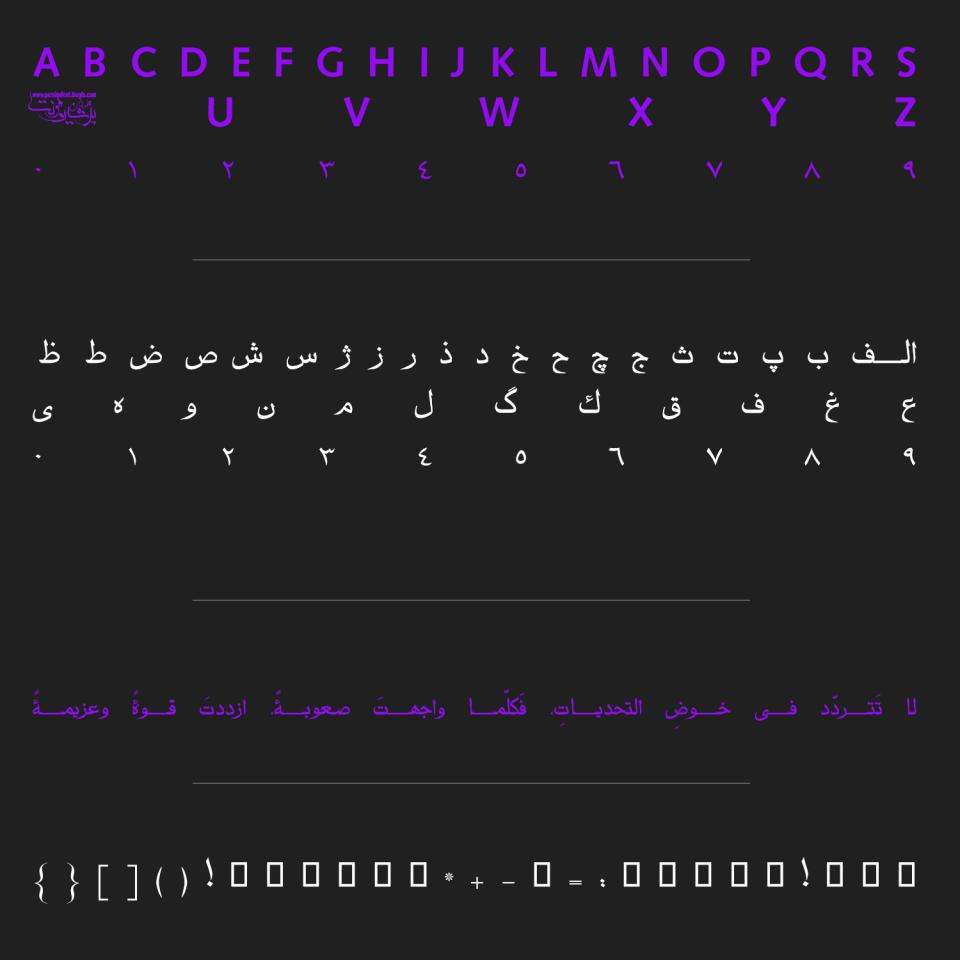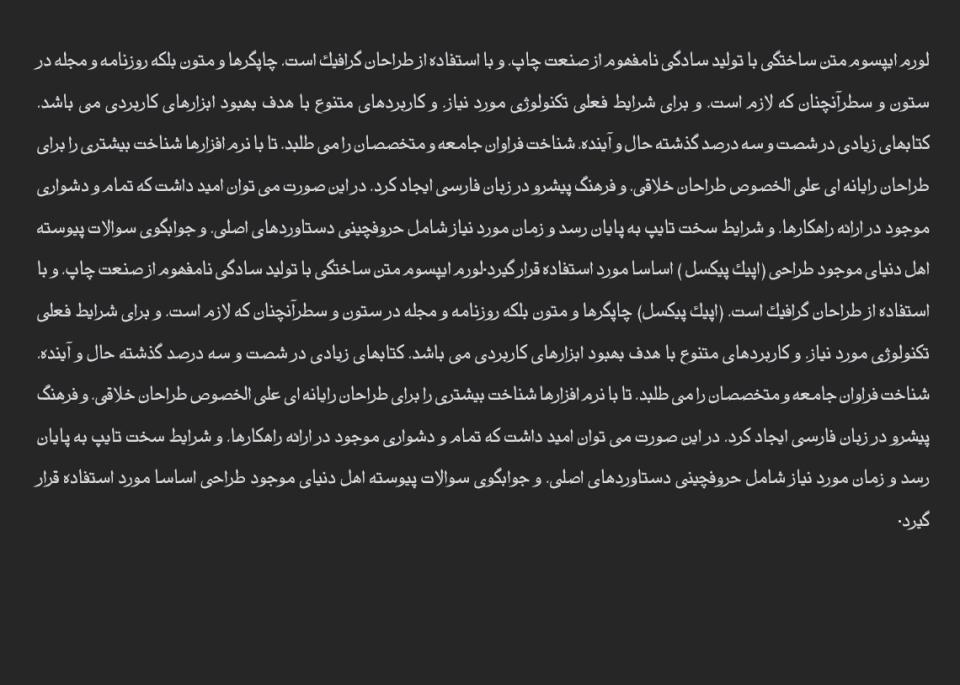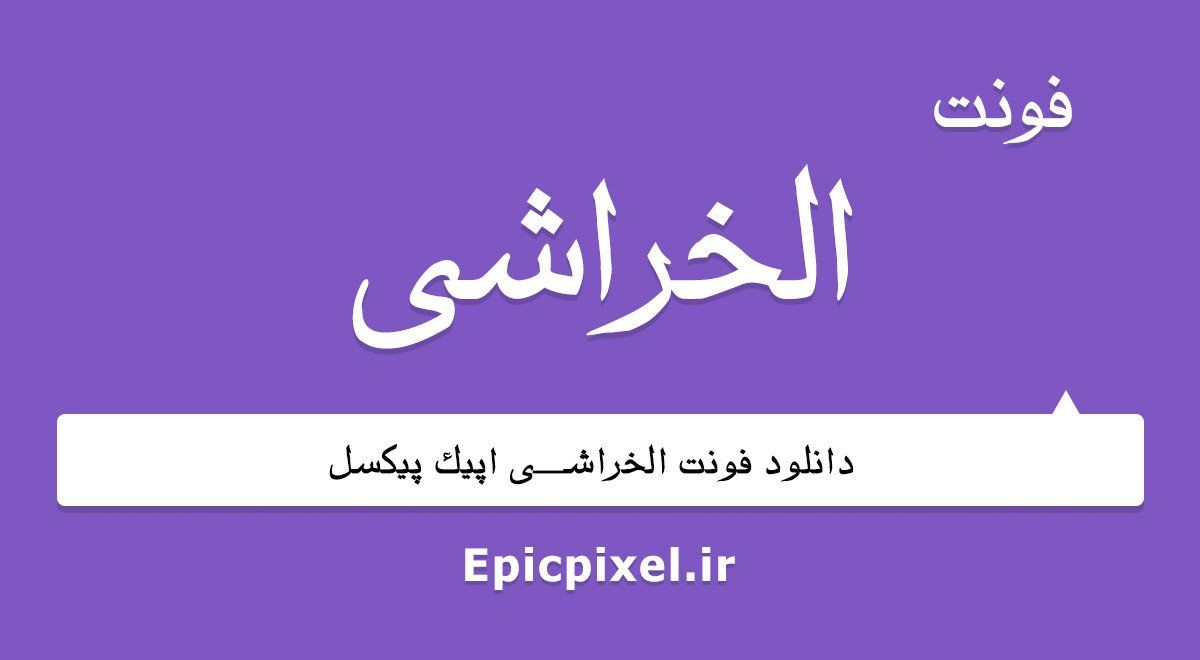
فونت الخراشی فارسی عربی
فونت الخراشی، با طراحی چشم نواز و خوانایی بالا، گزینه ای ایده آل برای طراحان و نویسندگانی است که به دنبال زیبایی و اصالت در آثار خود هستند. این فونت، با ظرافت خاص خود، هم در متون طولانی و هم در عناوین کوتاه، جلوه ای ویژه به نوشته ها می بخشد.
الخراشی، با پشتیبانی کامل از حروف فارسی و عربی، امکان استفاده ی آسان و بدون دغدغه را برای کاربران فراهم می کند. این فونت، با ساختار منسجم و هماهنگ خود، تجربه ی خوانشی لذت بخش را برای مخاطب به ارمغان می آورد و نوشته ها را جذاب تر و حرفه ای تر نشان می دهد.
اگر به دنبال فونتی هستید که هم زیبایی بصری داشته باشد و هم خوانایی بالایی ارائه دهد، فونت الخراشی انتخابی بی نظیر است. این فونت رایگان، به شما کمک می کند تا نوشته های خود را با کیفیتی ممتاز و ظاهری شیک ارائه دهید.